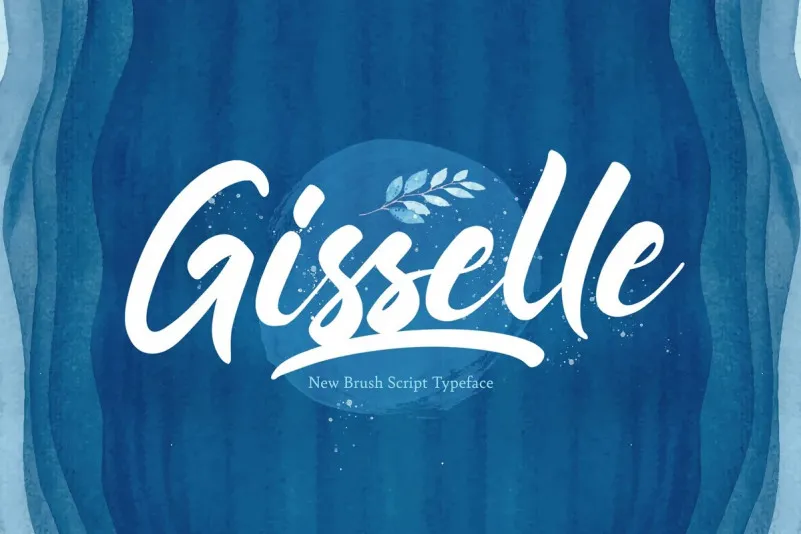
Gisselle Script Font – Fonte Grátis
Gisselle Script Font
Gisselle Script Font é uma elegante escolha para quem busca uma fonte script que transmite estilo autêntico e delicado. Esta fonte foi criada com a intenção de oferecer um toque refinado e sofisticado, perfeito para projetos pessoais ou profissionais. Seu design elaborado e carinhosamente escrita permite que suas criações se destacuem, dando uma sensação única e inconfundível aos seus trabalhos. Ideal para designers gráficos que buscam trazer um toque singular ao seu próximo projeto, Gisselle Script é perfeita para criar designs únicos, incrivelmente distintos e de alto nível. Seu estilo moderno e sofisticado mantém-se fiel através dos tempos, garantindo que seja uma fonte versátil que nunca sairá de moda. Adquira sua própria cópia e veja como essa font pode transformar suas criações em verdadeiros trabalhos de arte.